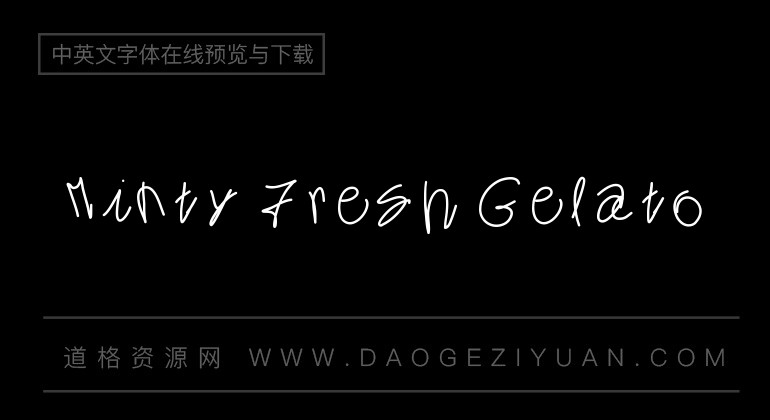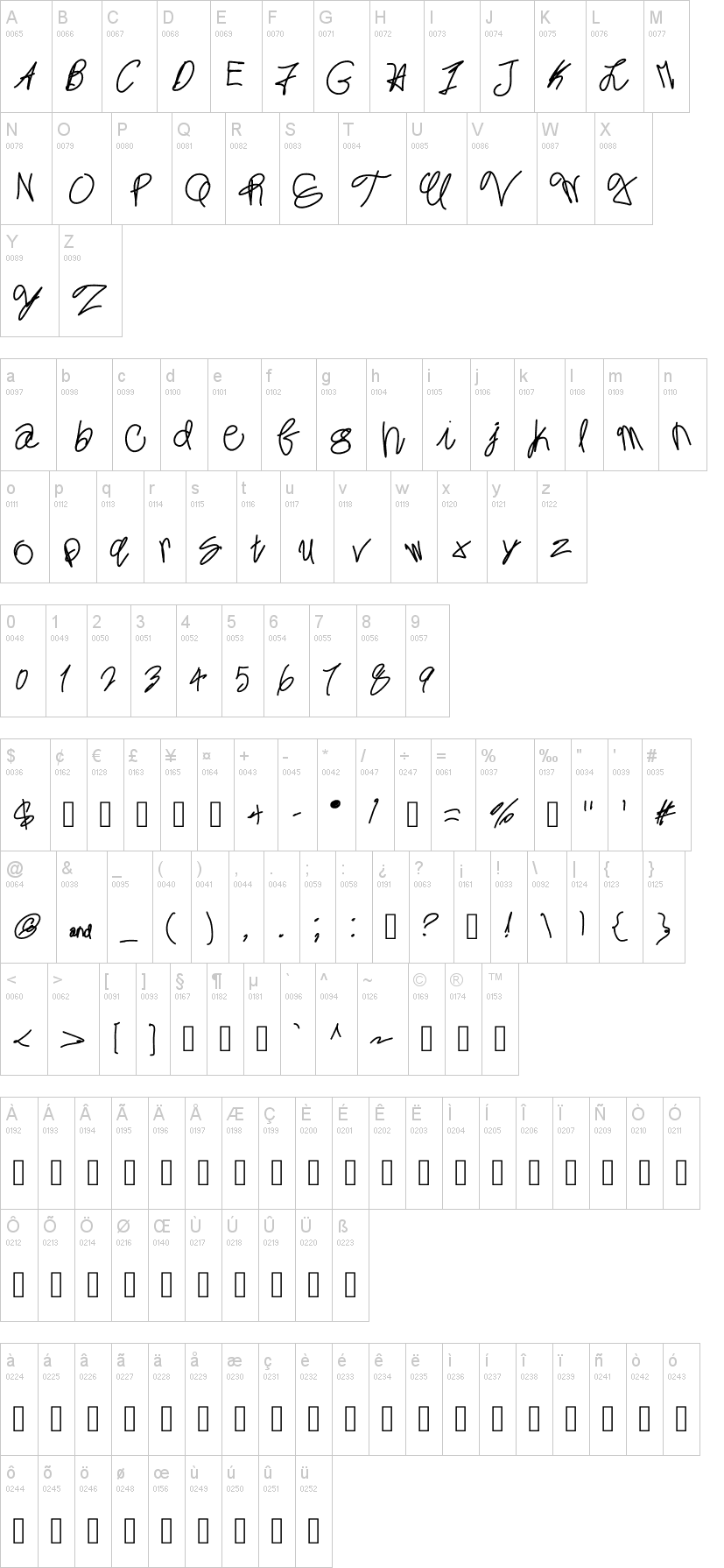
Minty Fresh Gelato 字体是一种现代风格的手写字体,其设计风格独特,具有轻松,活泼和清新的感觉。该字体的字形是基于手写的草书风格设计的,相比其他手写字体,它更加简洁和规整,让读者感觉更加清新舒适。 Minty Fresh Gelato 字体主要使用在一些印刷品、网站、广告和海报等设计领域。它的设计风格适合用于传达一些轻松欢快的信息,比如关于食品、娱乐、健康、美容等方面的内容。 该字体支持多种语言和符号,可以很好地适应全球市场的需求。此外,该字体也可以免费下载和使用,因此非常受到设计师的欢迎。内容介绍
Minty Fresh Gelato是一款非常不错的手写艺术字体,具有很好的视觉感,适合于文化类的宣传设计、商业类品牌的广告和产品包装设计以及个性化文字排版等较多场景。